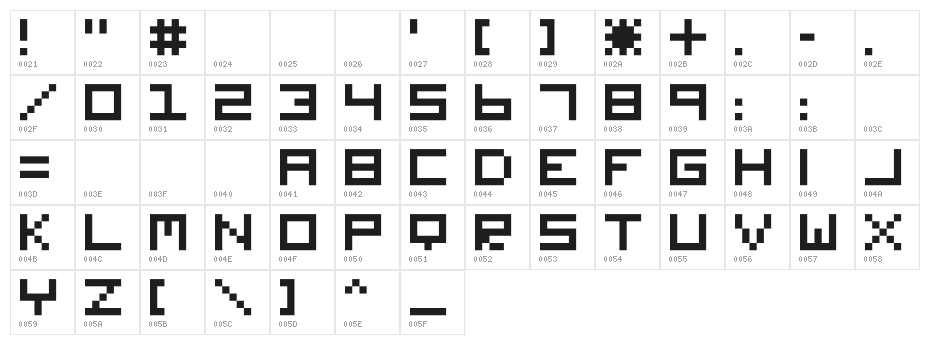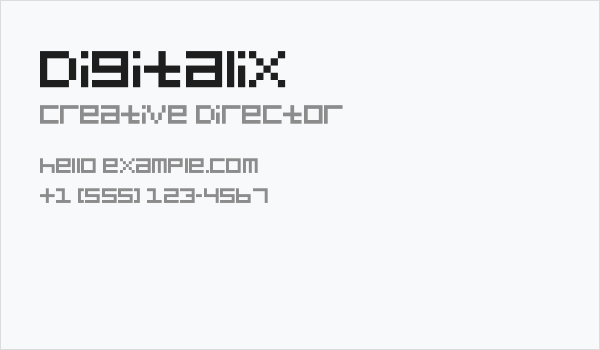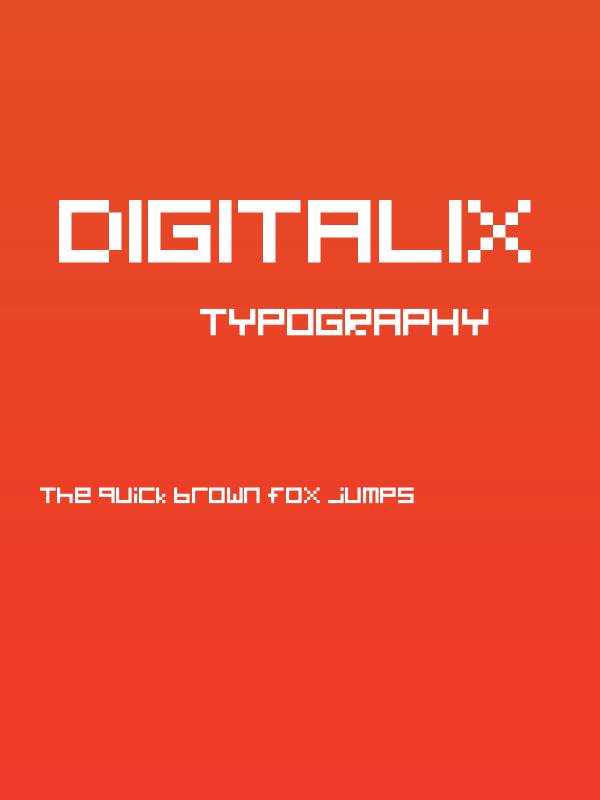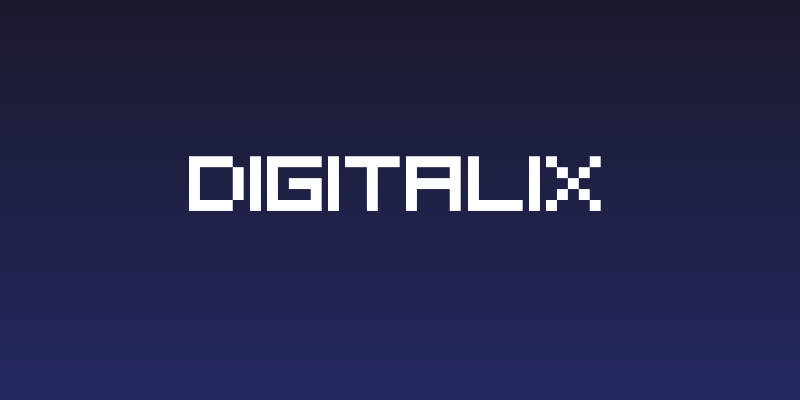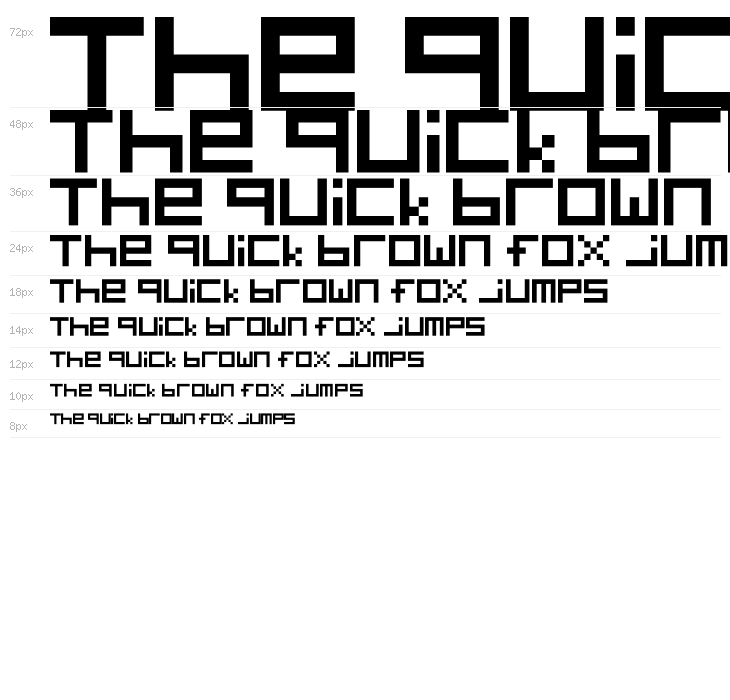
Digitalix Font
| Stile generale | Modern, Retro |
| Caso d'uso | Headlines, Logos, Digital Art |
| Progetti proposti | Ideal for digital art, retro video game graphics, tech-themed posters, and websites with a vintage computer aesthetic. |